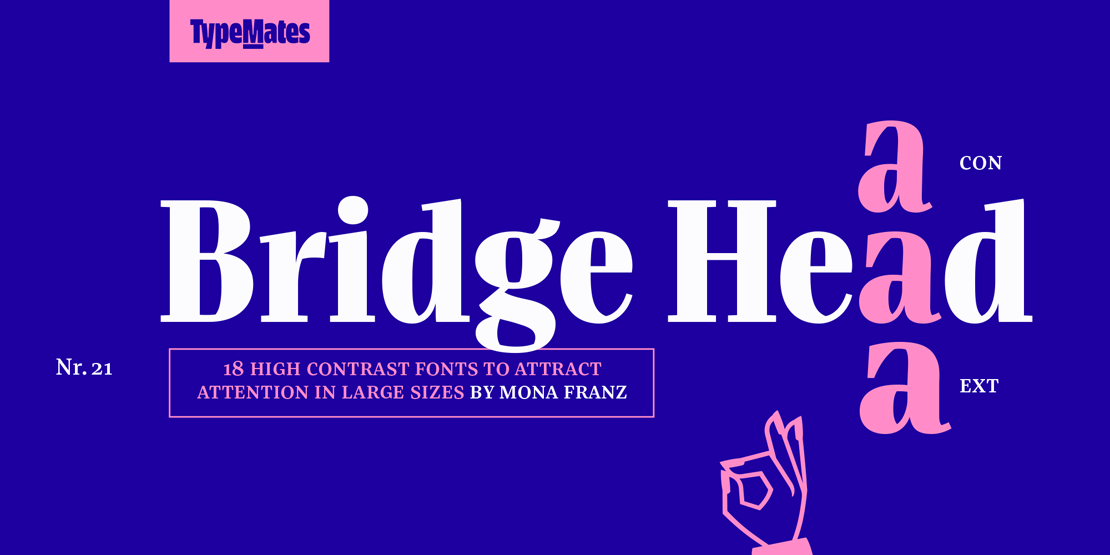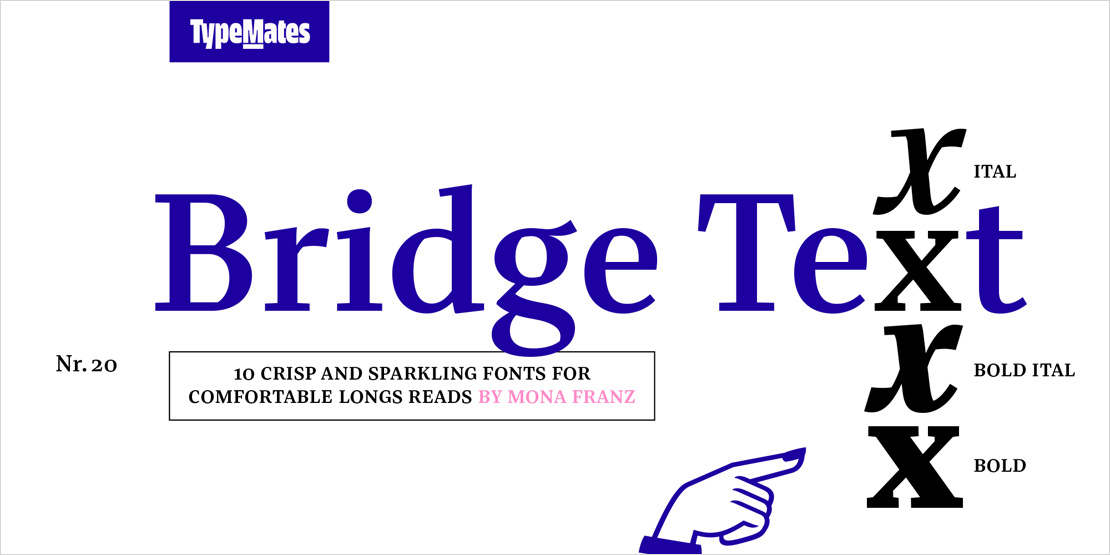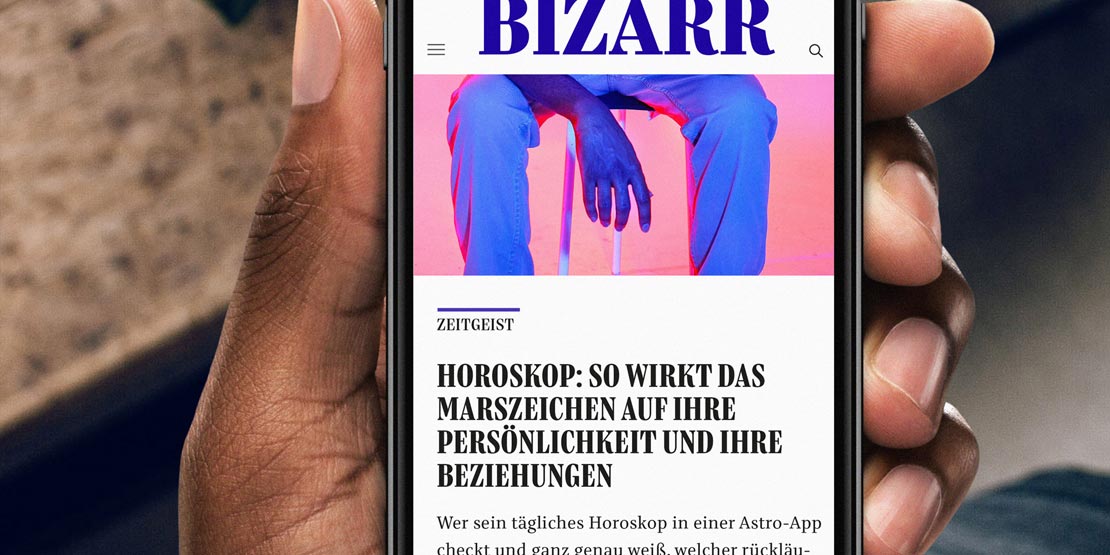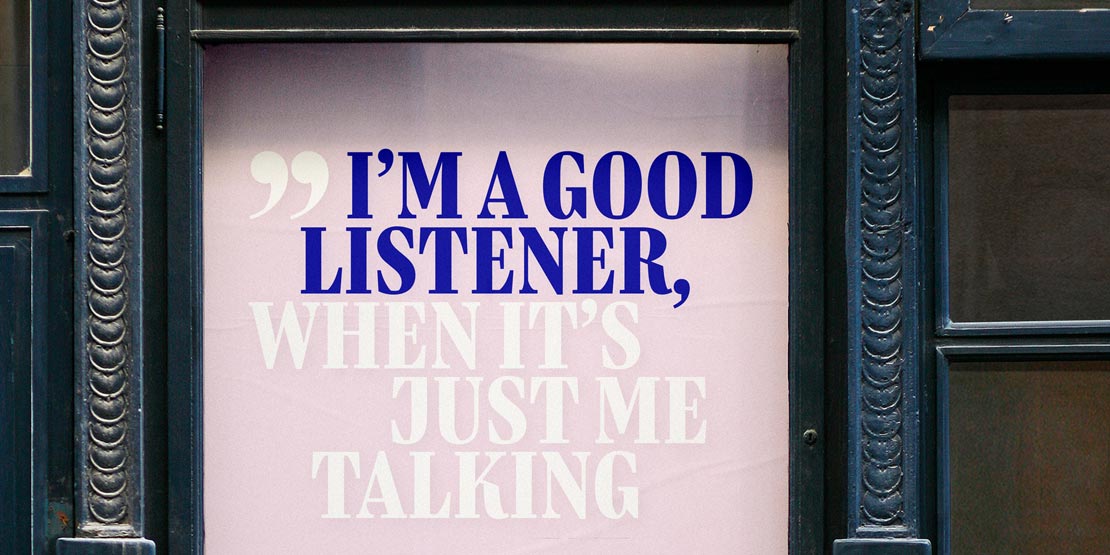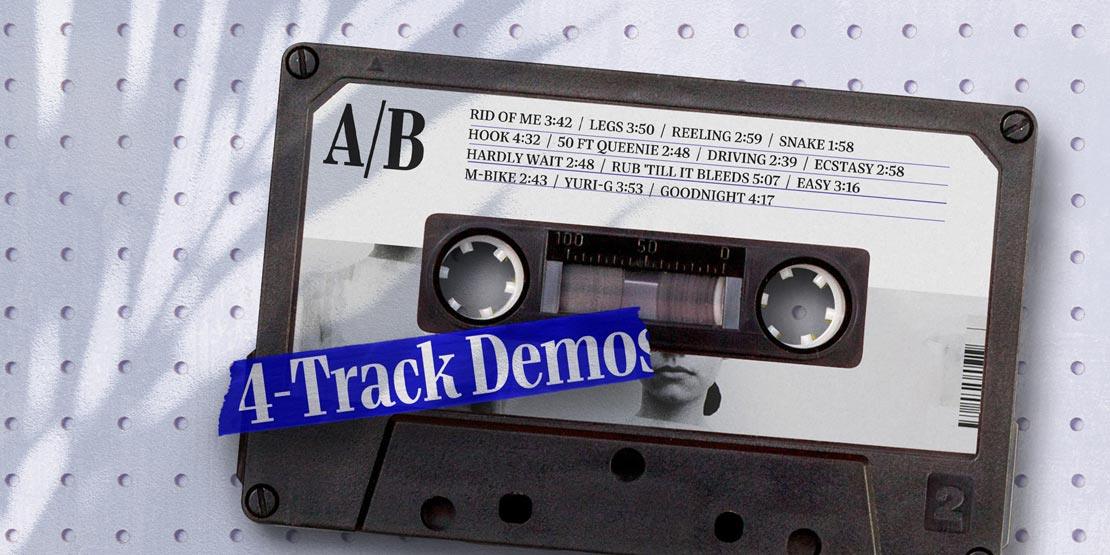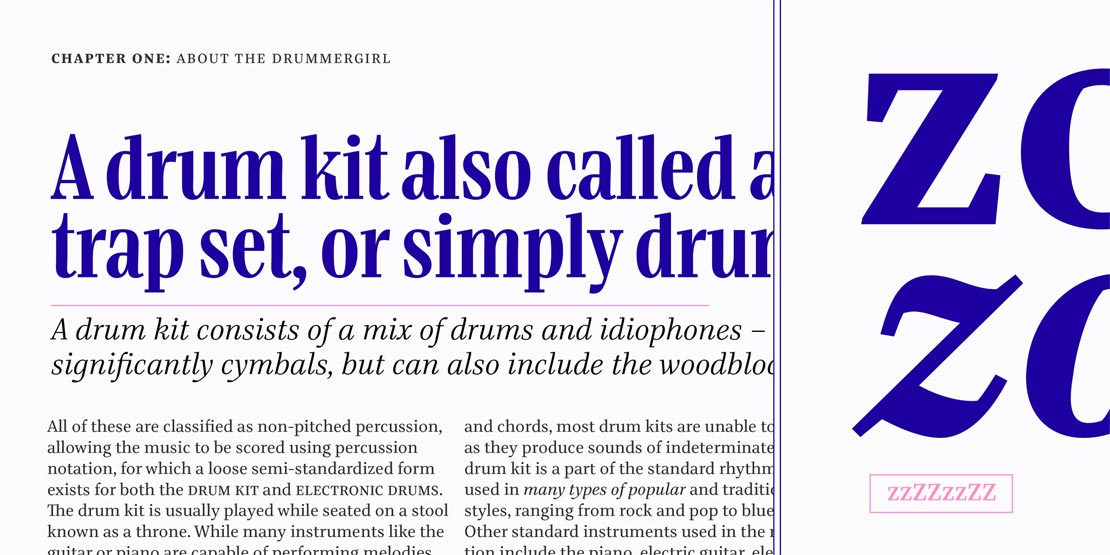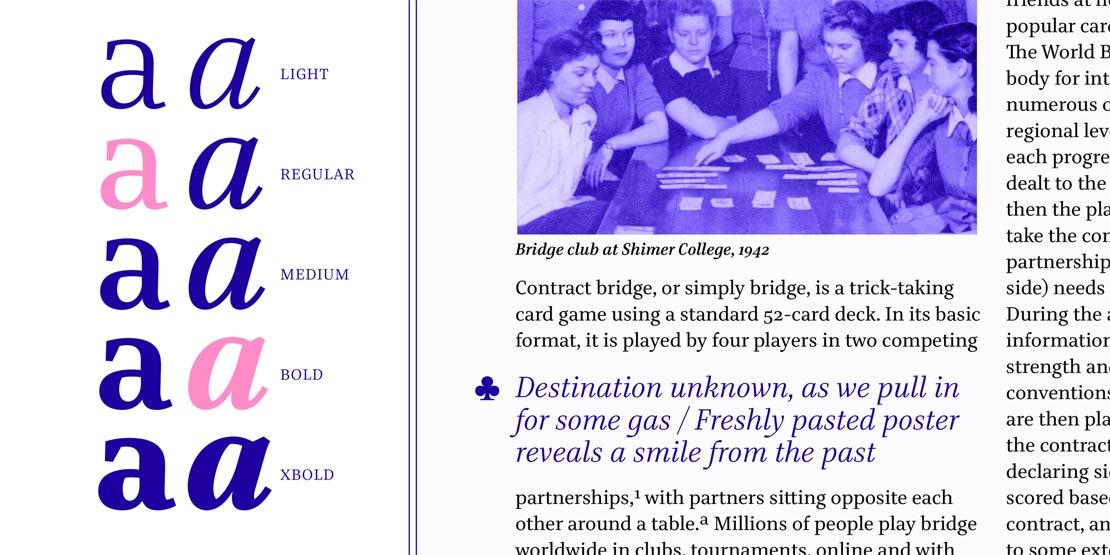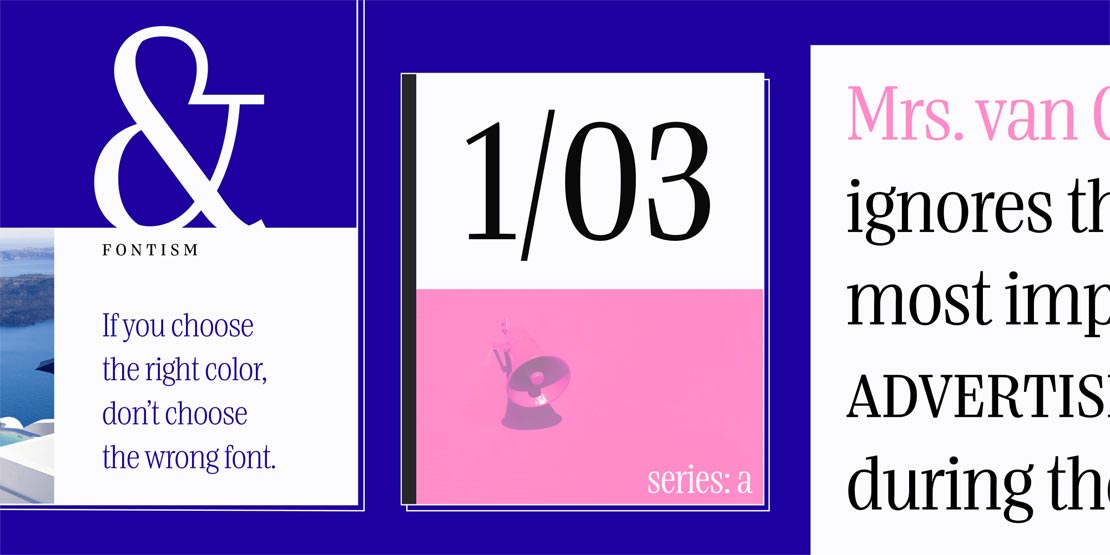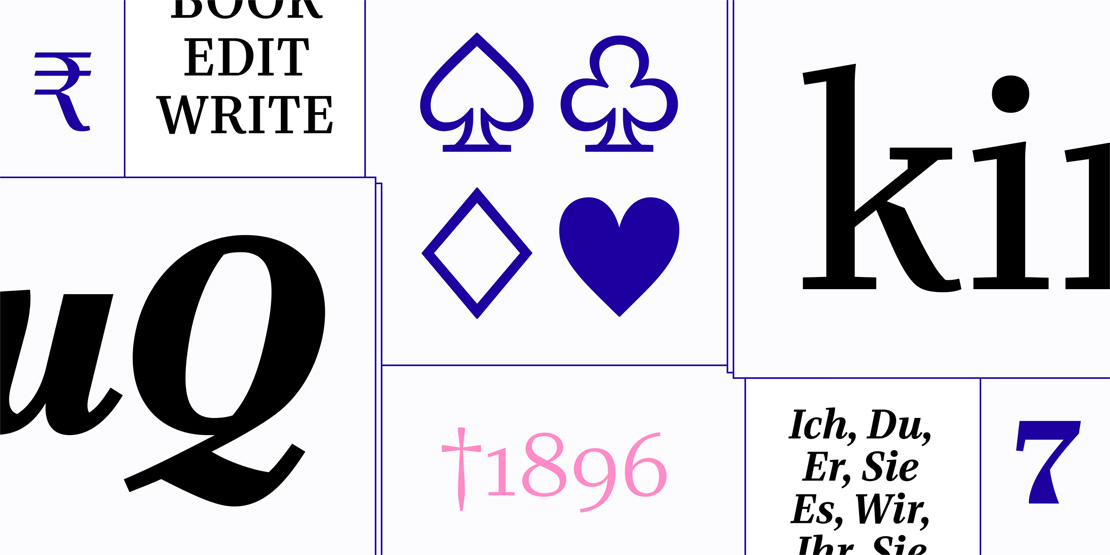
Schriften-Duo Bridge Head & Bridge Text von TypeMates
Ein Duo für Prosa und komplexes typografisches Editorial oder Corporate Design: »Bridge Head« und »Bridge Text« sind neu bei TypeMates erschienen.
Die Schriftsippe besteht aus zwei Familien – Text und Head – für ein angenehmes Leseerlebnis und passende ausdrucksstarke Überschriften. Ein flexibles Schriftsystem, mit dem eine Brücke zwischen Print-Publishing und digitalen Medien geschlagen werden soll.
Bridge Head für Titel
Mit drei verschiedenen Breiten und sechs Gewichten bietet »Bridge Head« die passenden Stimmlagen für ausdrucksstarke Titel. Außerdem wurde mit Bridge Text ein Duettpartner entwickelt, um im gemeinsamen Einsatz Geschichten zu schreiben und komplexe typografische Layouts im Editorial und Corporate Design zu kreieren.
Text-Layouts mit Bridge Text
»Bridge Text« ist eine kantige Schrift für Editorial-Design, die Rhythmus und Klarheit in umfangreiche Text-Layouts bringen soll. Mit angenehmem Charakter, leserlichem Schriftbild und asymmetrischen Punzen ergänzt »Bridge Text« die grafischen Qualitäten der »Bridge Head« auch in kleineren Größen.